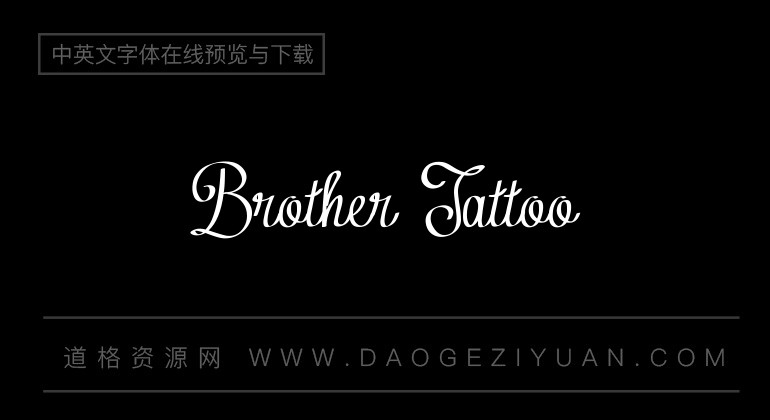
Brother Tattoo
Brother Tattoo 是一款欧美风格的手写字体,它拥有优雅的线条和温暖的氛围,可以给人一种放松、自由的感觉。它拥有细腻的笔画,可以用来制作海报、海报、卡片、标识等。它的字型风格清新,容易读写,可以让你的文字充满活力,给你的设计带来温暖的感觉。
Brother Tattoo是一款非常不错的手写艺术字体,具有很好的视觉感,适合于文化类的宣传设计、商业类品牌的广告和产品包装设计以及个性化文字排版等较多场景。
Brother Tattoo字符映射图